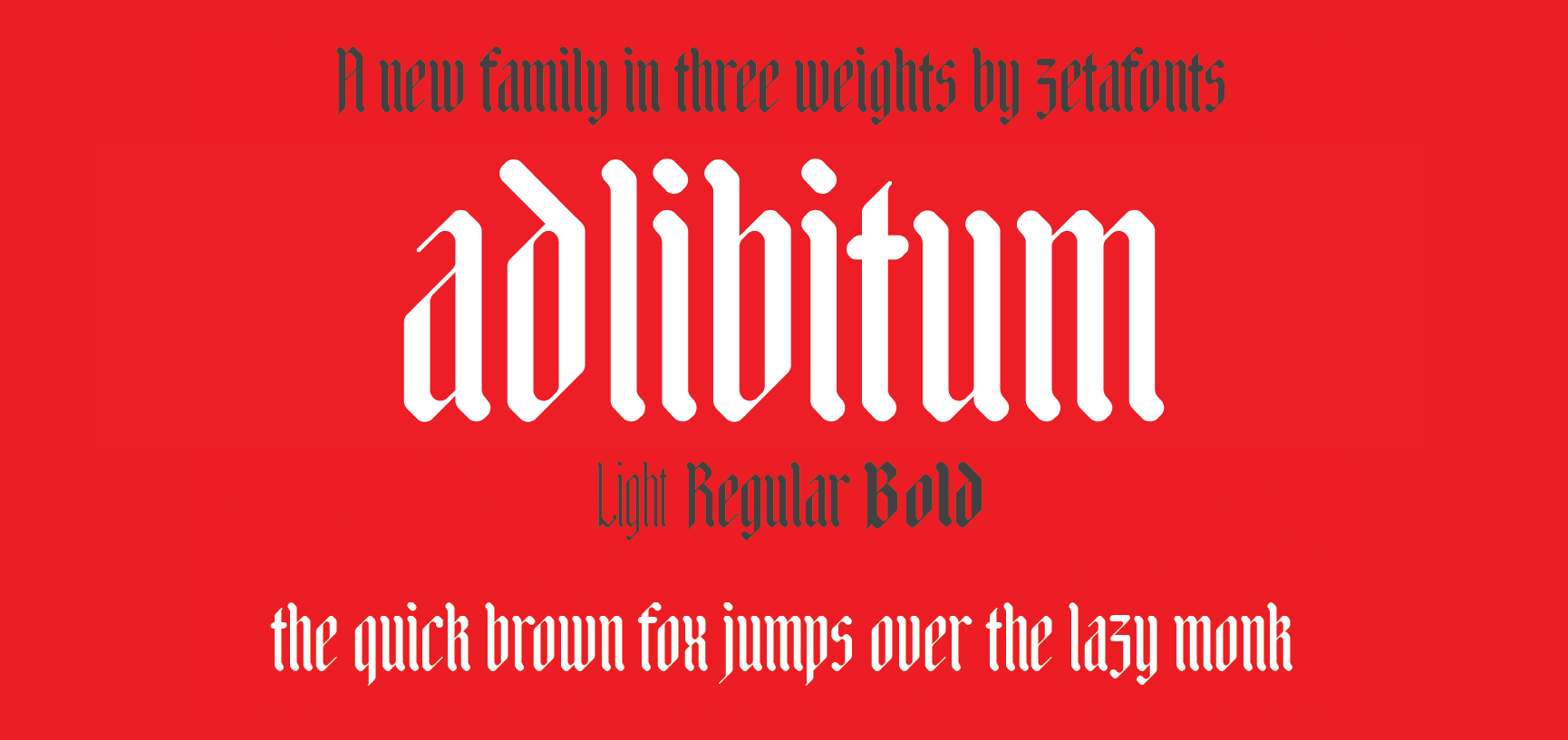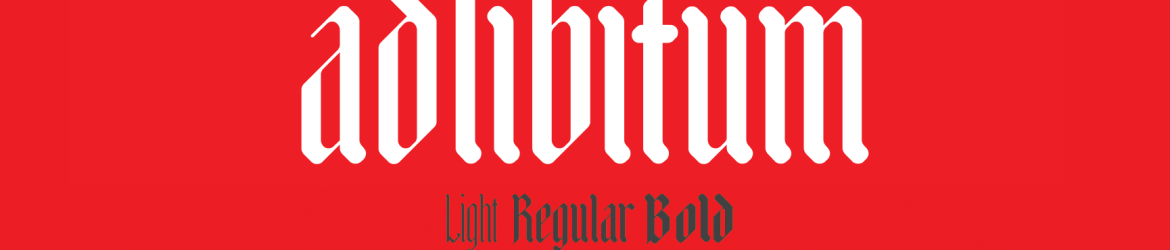
Adlibitum é uma família tipográfica blackletter para uso exibicional, desenhada pelo designer Hamilton. Inspirado nos caracteres do script textura medioieval tradicional, esta fonte traz um revival contemporâneo de texto antigo, oferecendo um design geométrico com ângulos a 45 graus e bordas suaves. Com seu forte destaque vertical e set de caracteres extenso que abrange vários idiomas europeus, Adlibitum também inclui suporte para ligaturas em formato OTF, permitindo uma experiência tipográfica mais avançada e personalizável. Ideal tanto para aplicações em impressões digitais quanto em layouts tradicionais, Adlibitum é uma escolha atraente para quem busca um visual elegante e sofisticado que lembra o passado ao mesmo tempo que se mantém no rumo do moderno.